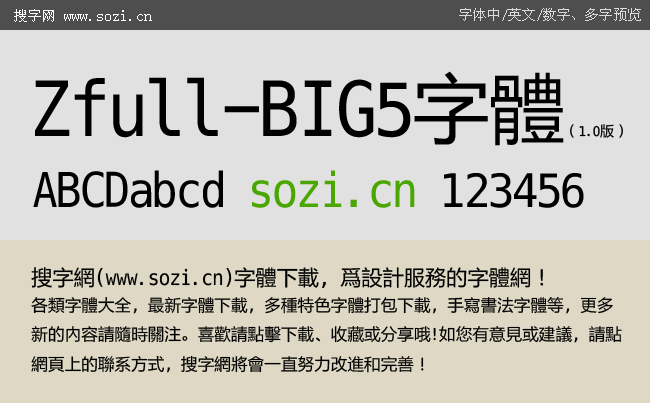
正體(繁)中文點(diǎn)陣字Zfull-BIG5
搜字網(wǎng)提供一款正體(繁)中文點(diǎn)陣字Zfull-BIG5中文字體下載,正體(繁)中文點(diǎn)陣字是一款字形端莊的中文藝術(shù)字體,字體簡(jiǎn)潔端正,莊重大方。GBK碼收錄字體更全,適合應(yīng)用于廣告設(shè)計(jì)、名片設(shè)計(jì)、包裝印刷、產(chǎn)品設(shè)計(jì)等應(yīng)用。